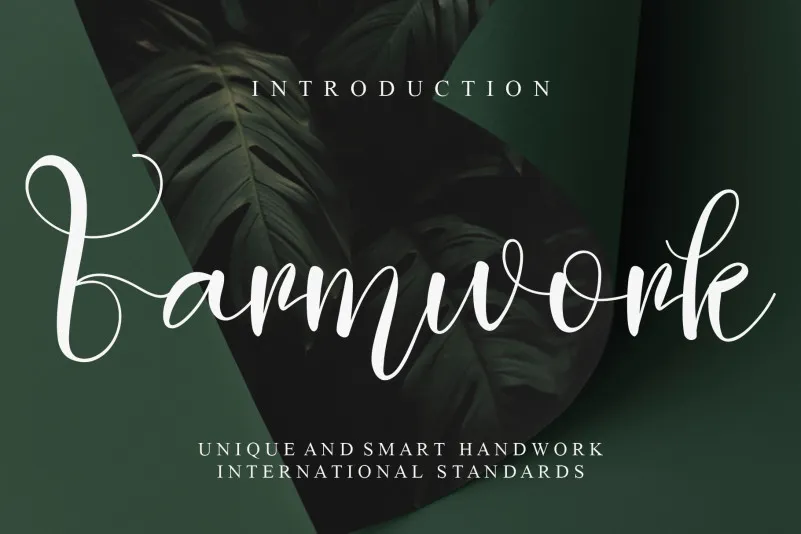
Farmwork Font – Download Grátis
Esta é uma especial e criativa fonte escrita a mão com caracteres elegantes que impressionam com seu estilo! A Farmwork Font é perfeita para adicionar um toque suave a etiquetas, designs de produtos, marcas d’água, fotografias e muito mais. Composta por letras cuidadosamente elaboradas, essa fonte traz uma atmosfera envolvente e natural à sua obra. É perfeitamente adaptável para diversas aplicações gráficas, tornando-a uma escolha ótima tanto para designers quanto para aqueles que buscam um toque de elegância em seus projetos. Não importa o campo ou projeto em que você esteja trabalhando, a Farmwork Font certamente encontrará seu lugar e será capaz de dar um tom único a qualquer trabalho.